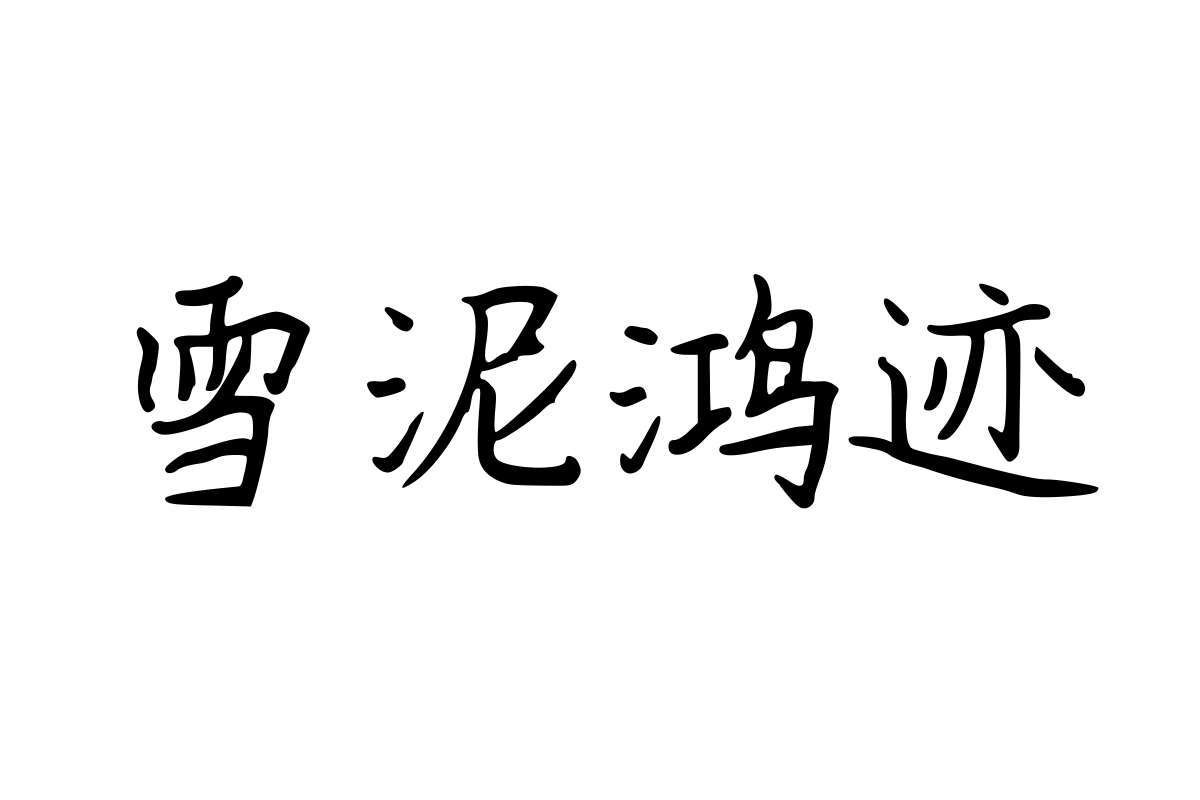
思雨温柔浅尝是一款具有艺术感和现代感的字体,它以其独特的设计和风格吸引了众多用户的喜爱。这款字体采用了简洁而流畅的线条,使得整个字形显得优雅而富有层次感。
思雨温柔浅尝的笔画粗细适中,既不会过于夸张也不会过于简单,给人一种舒适的感觉。这种平衡的设计使得整个字体看起来既时尚又不失传统韵味。
此外,该字体还具有一定的可读性,无论是在哪种场合都能轻松阅读。这使得思雨温柔浅尝成为了一种非常实用的设计选择。
总的来说,思雨温柔浅尝是一款非常适合用于各种设计场景的字体,无论是用于印刷品、网页还是社交媒体,都能展现出其独特的魅力。